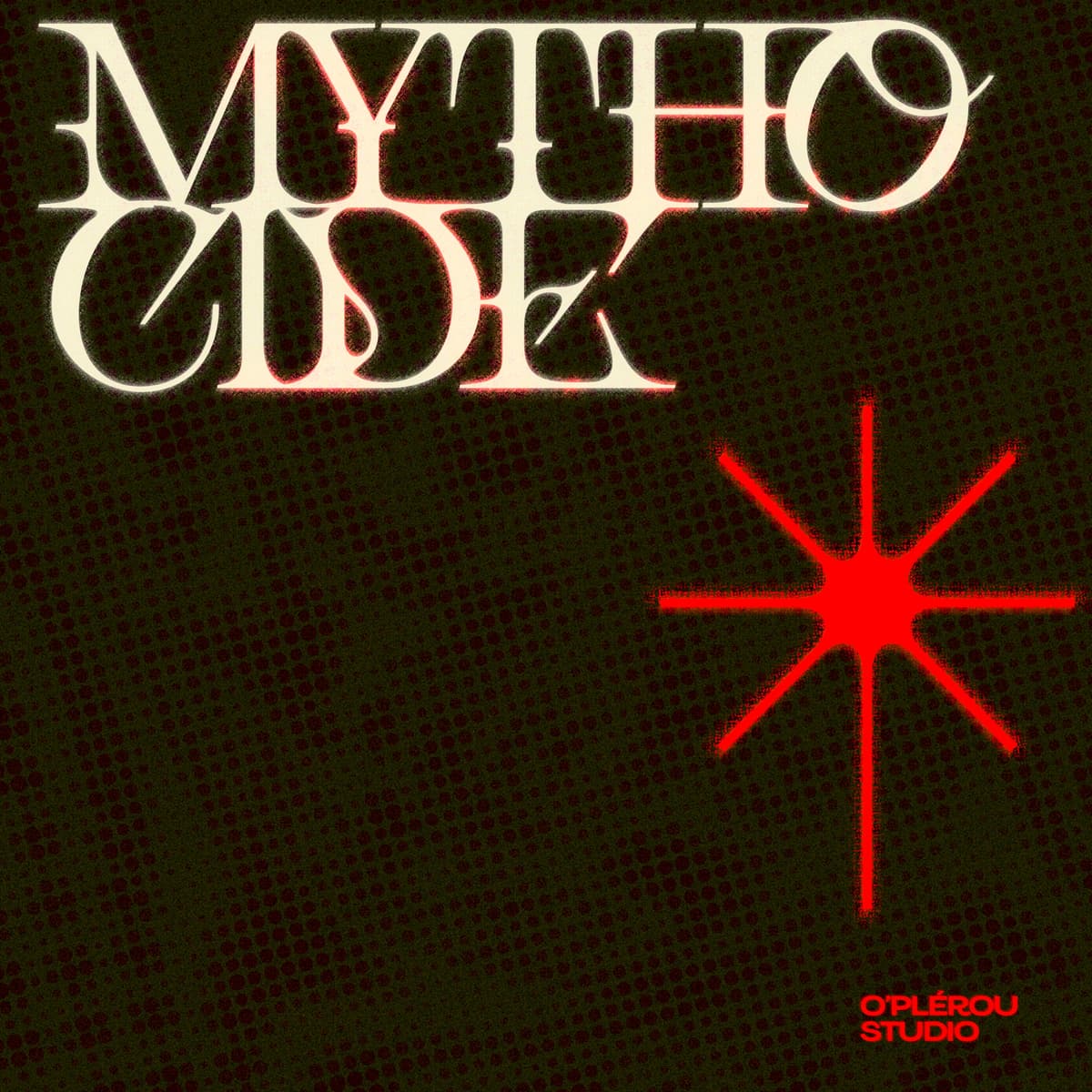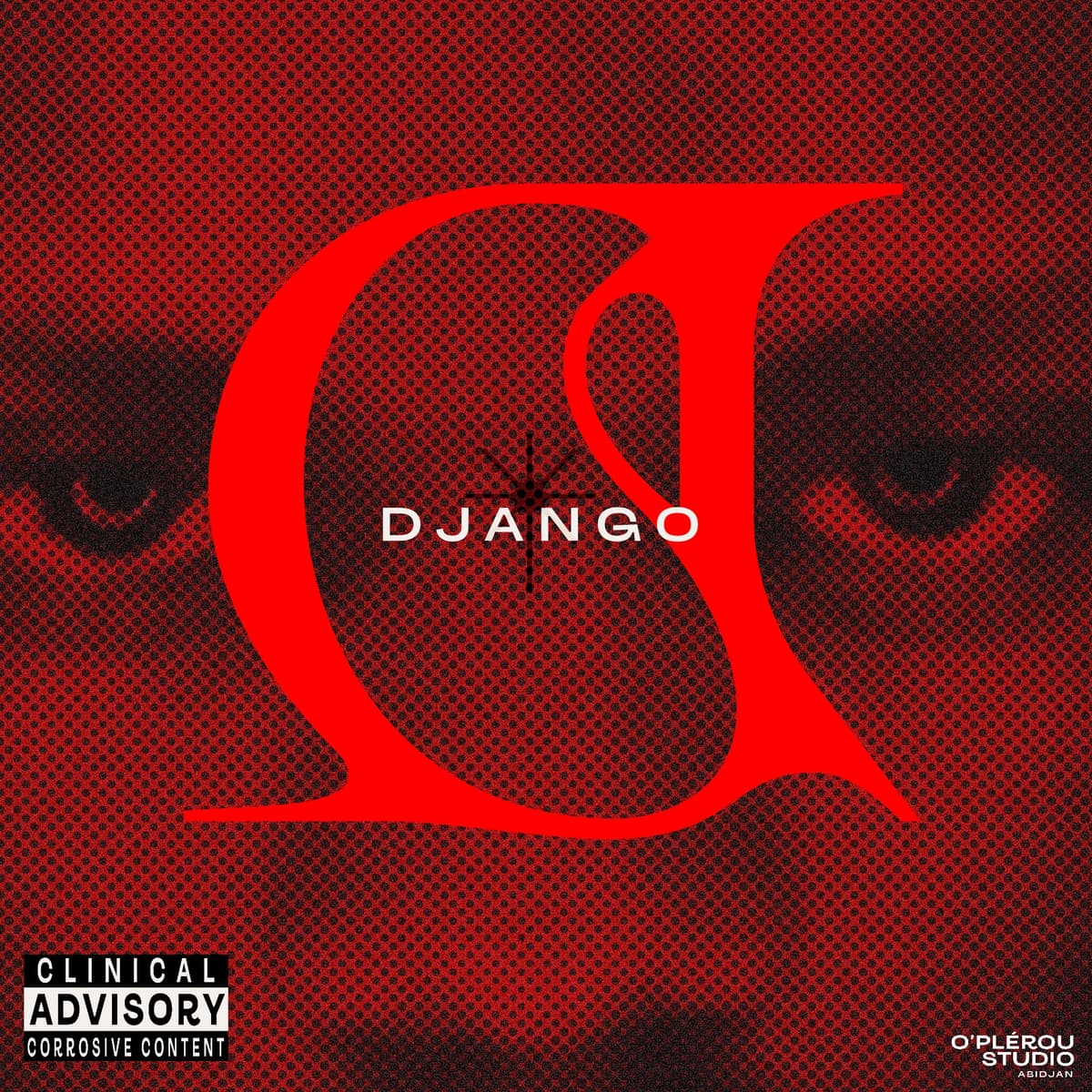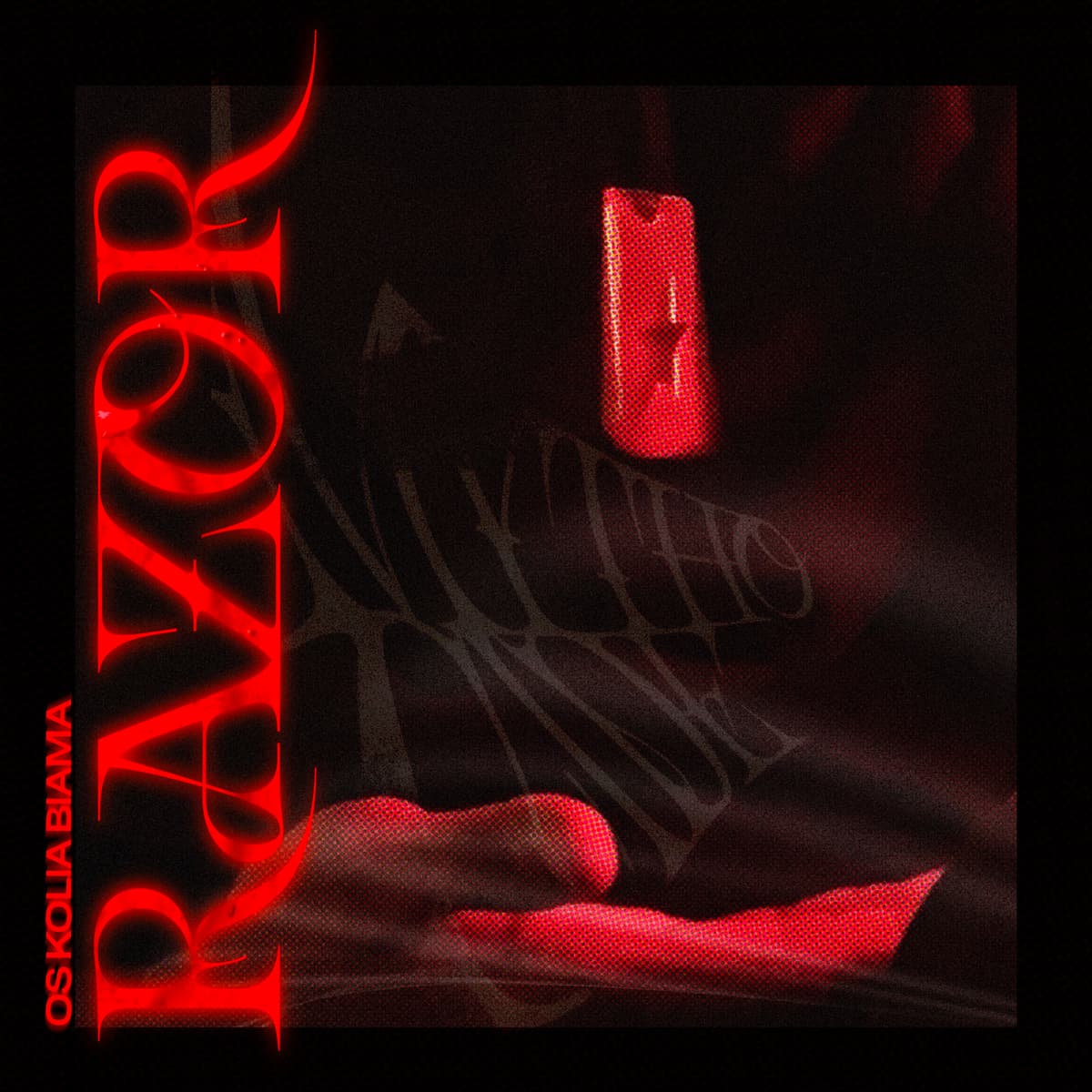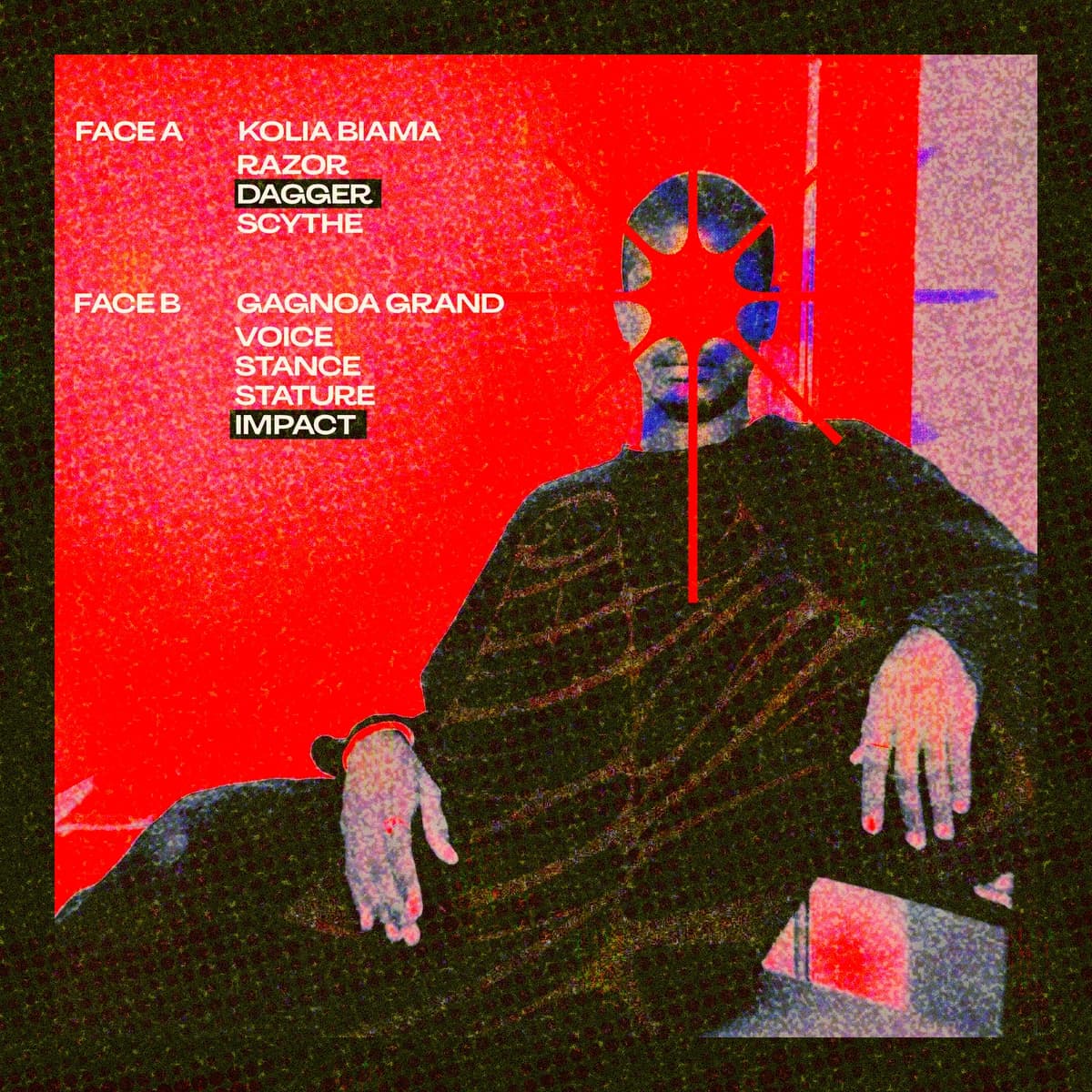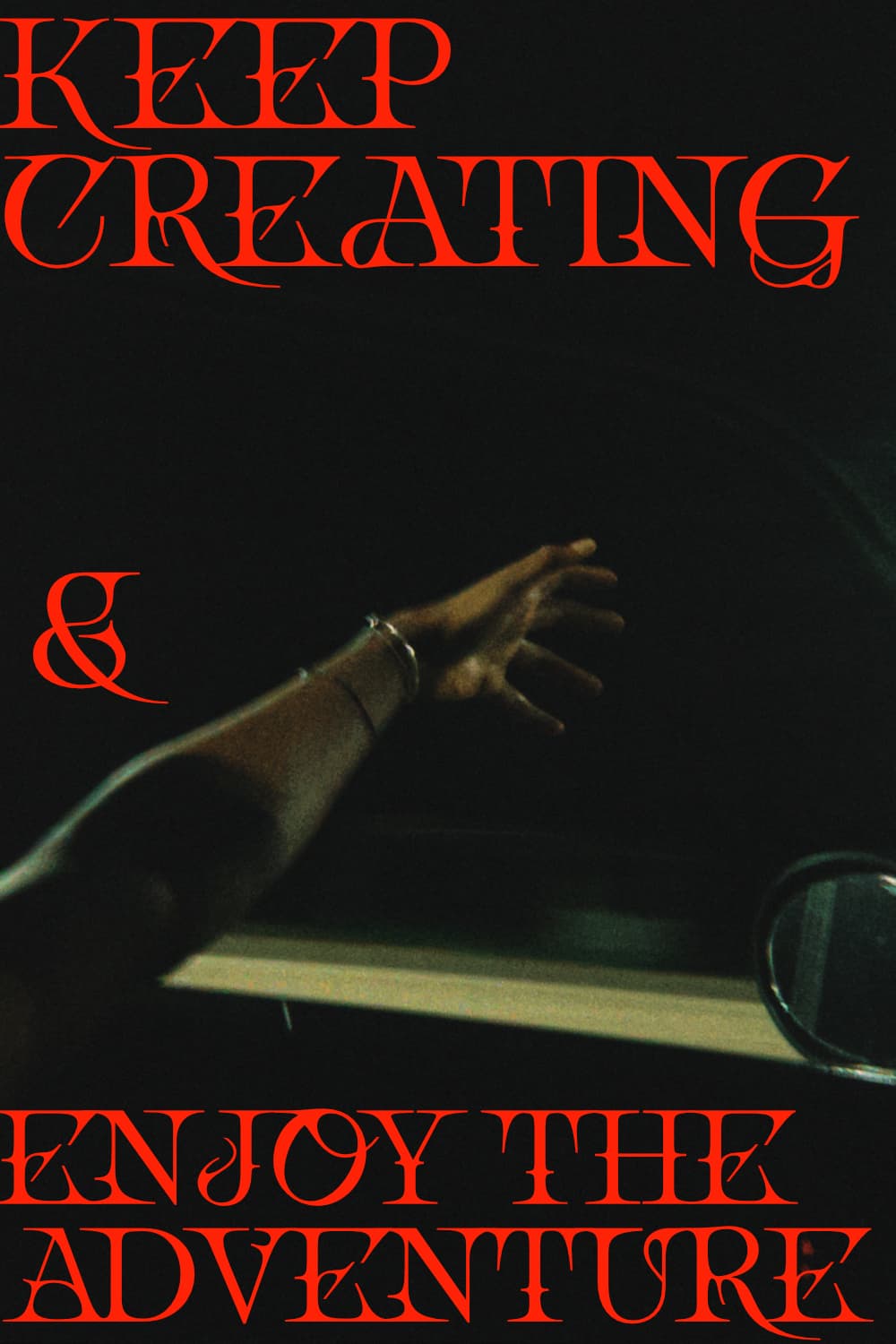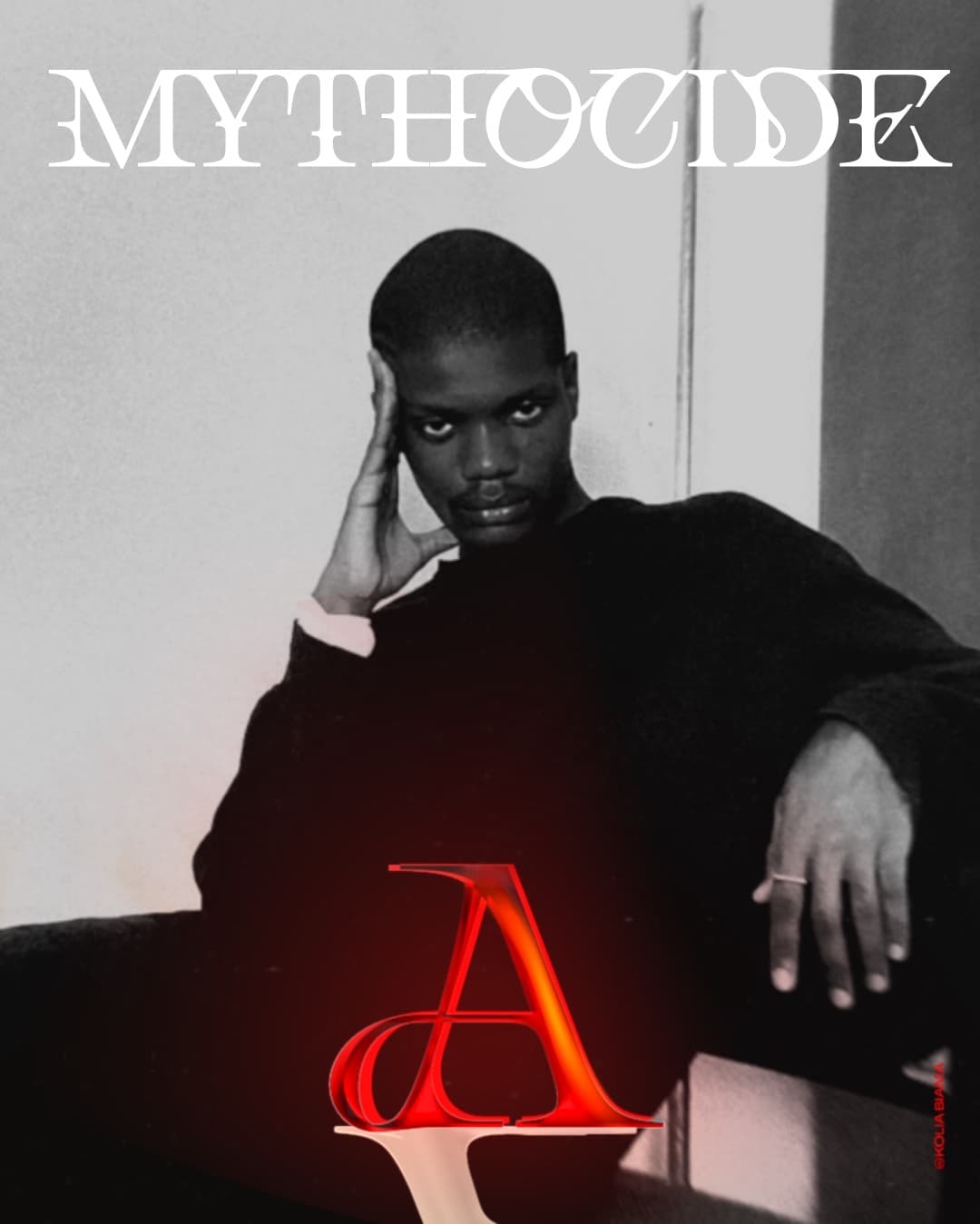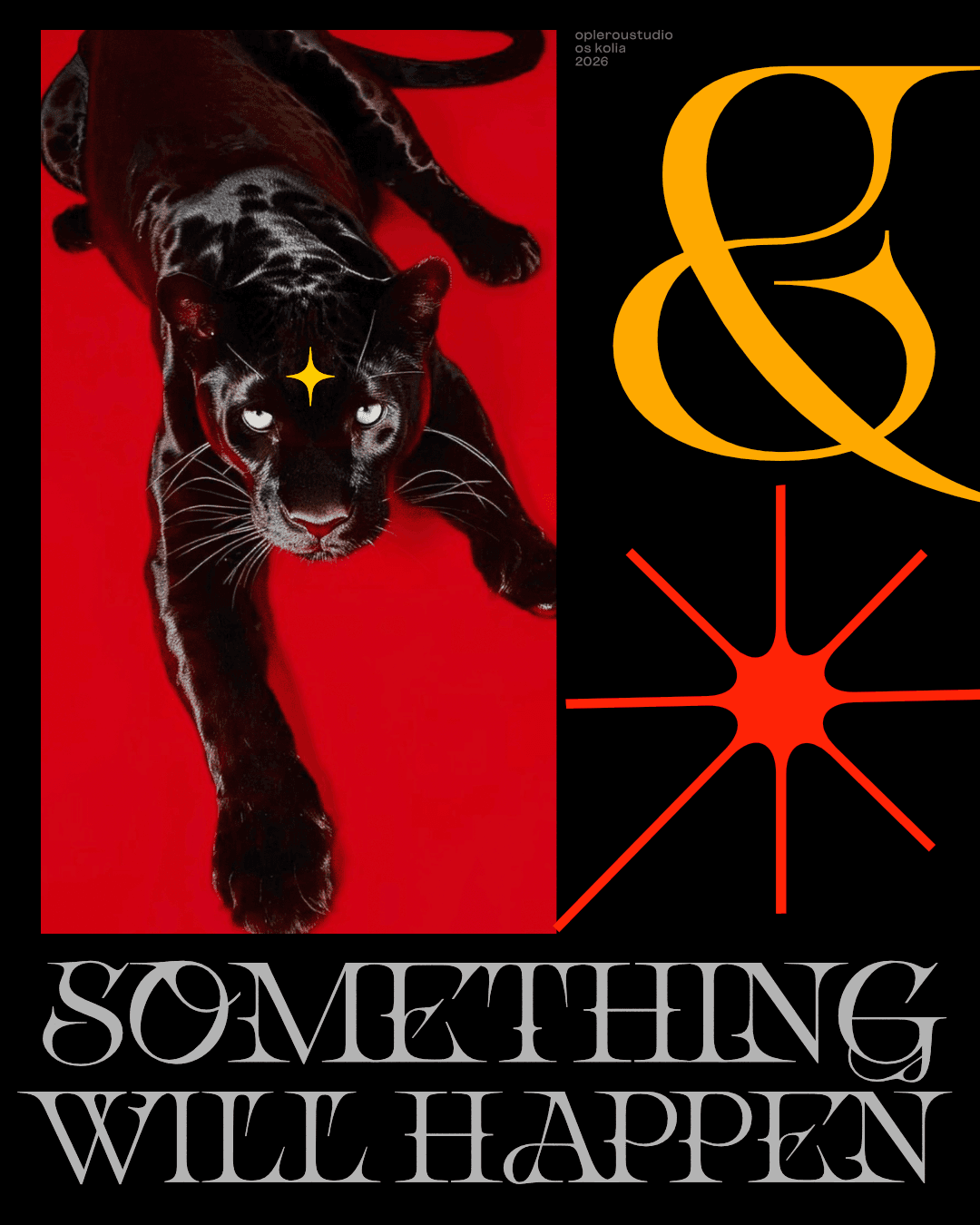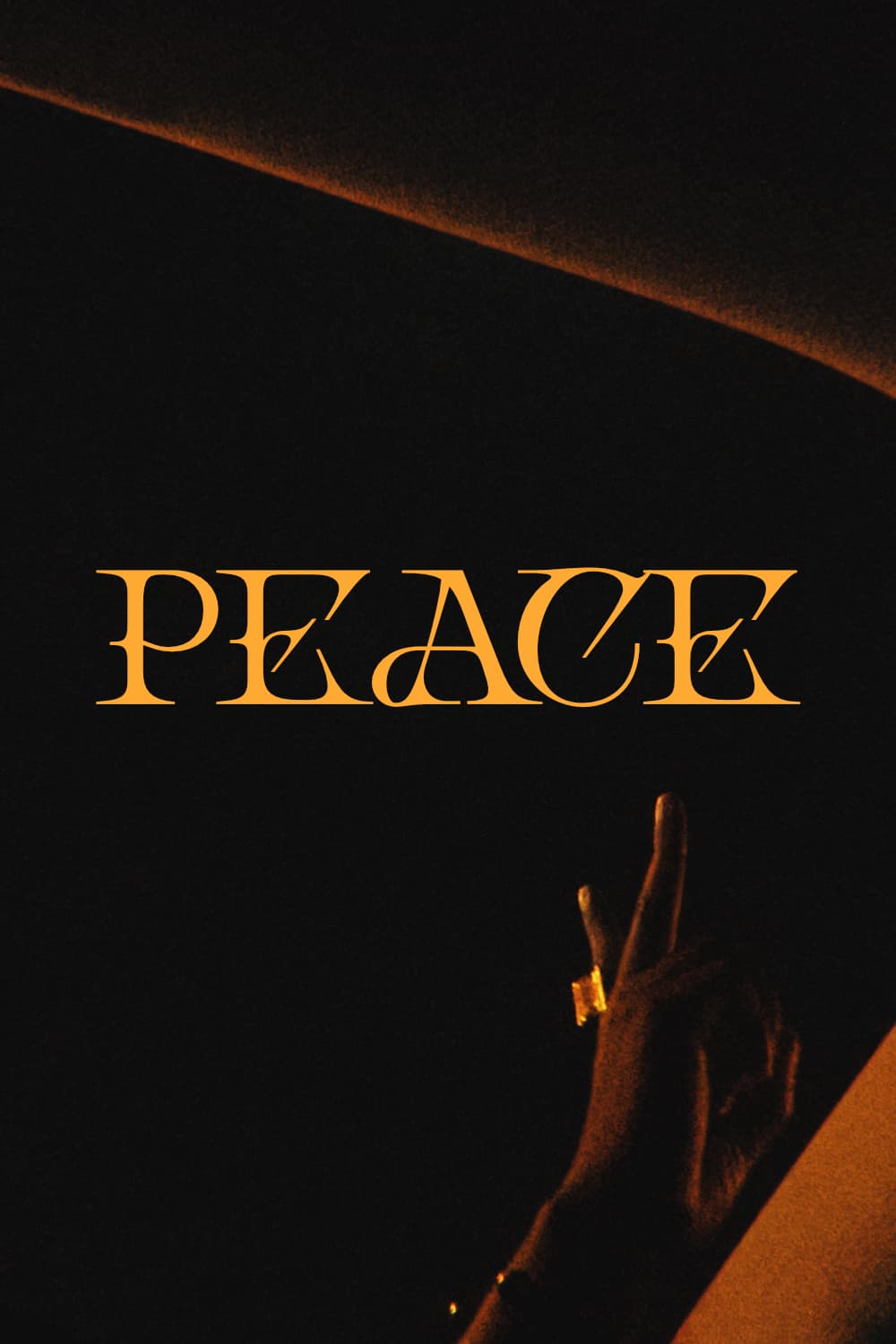
Biama méchant méchant.
CORROSIVE.
Biama méchant méchant.
CORROSIVE.
DANS LA PREMIÈRE CASE DE Kolia, UN FEU BRÛLE DEPUIS TROIS SIÈCLES. C'EST L'ÉNERGIE QU'INCARNE CETTE POLICE: UNE combustion QUI A COMMENCÉ, ET QUI VA JAHIN FINIR.
OS Kolia Biama est là pour tuer les histoires qui gardent petit·e. Elle incarne le moment où tu arrêtes d'être inoffensif, et assume d’être plus dangereux que prévu.